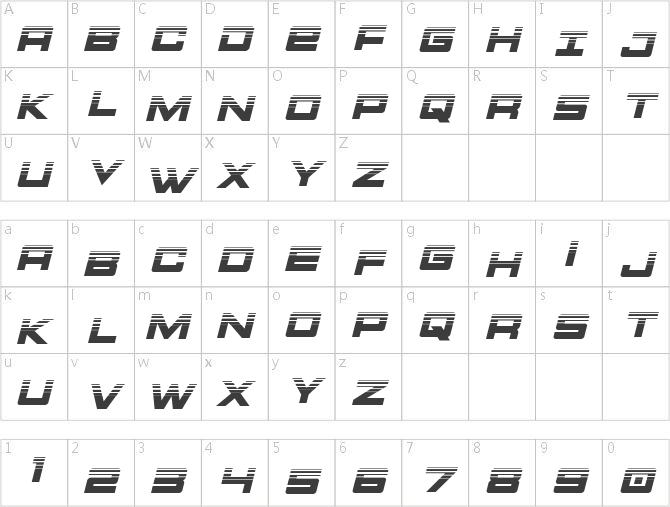
Montroc Halftone Italic 詳情頁
Montroc Halftone Italic字體字庫是一款讓人賞心悅目、百看不厭的英文字體,適合各類廣告和產(chǎn)品包裝設(shè)計應(yīng)用,字體大小0.04MB,格式為ttf字體,上傳用戶是afig,作者/版權(quán)方為未知